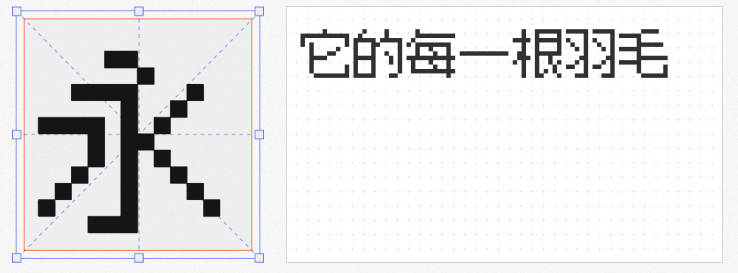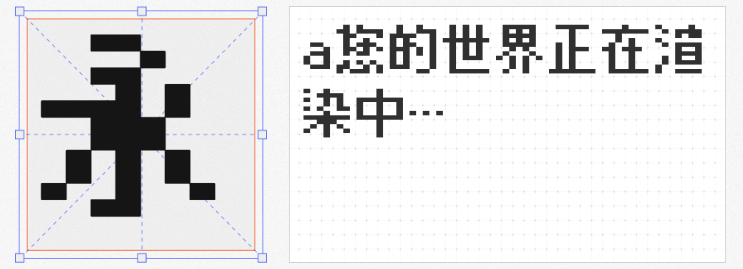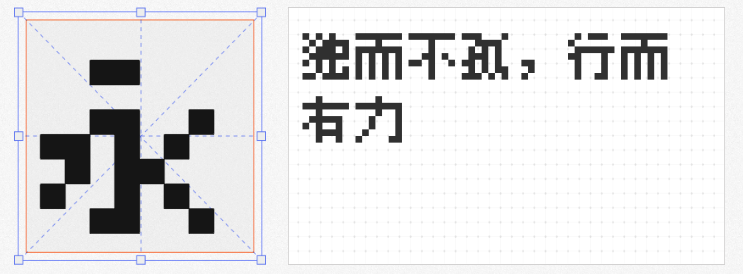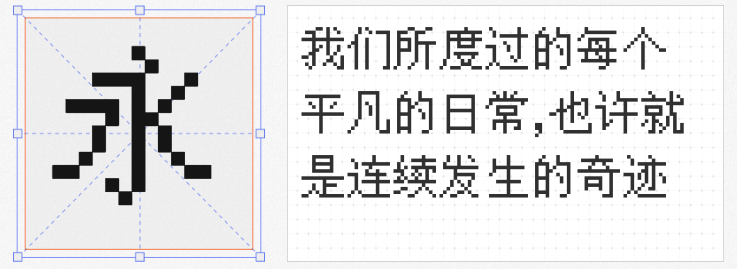
在游戏开发中,像素字体不仅是视觉风格的核心载体,更是构建沉浸式体验的关键元素。本文精选四款开源免费商用像素字体,从技术特性到应用场景,为开发者提供实用指南。
作为专为游戏设计的开源字体,方舟像素采用黑体无衬线风格,支持10/12/16px三种尺寸。其12px版本特别针对繁体中文(zh_TW)进行优化,完整覆盖中日韩统一表意文字扩展区,包含游戏界面常用的日文假名与韩文字符。字体采用SIL OFL 1.1协议授权,开发者可自由修改字形或嵌入商业游戏。在横版卷轴游戏中,该字体的等宽特性可确保对话框文字对齐,而12px的适中尺寸在4K分辨率下仍保持清晰锐利。
这款覆盖GB18030标准的自由字体,以13px尺寸成为RPG游戏对话系统的理想选择。其27842个汉字点阵经过手工优化,在1080P分辨率下呈现如印刷体般的清晰度。字体包含五组字号(9-12pt),开发者可根据UI层级灵活切换。在模拟经营类游戏中,13px宋体的衬线设计可增强菜单文字的可读性,而日文假名与韩文字符的完整支持,使其成为国际化发行的优选方案。
作为方舟像素的过渡方案,缝合怪通过合并多个开源字体实现8/10/12px三尺寸支持。其8px版本专为低分辨率设备优化,在320×240分辨率下仍能保持文字轮廓完整。在Roguelike游戏中,该字体的等宽模式可确保ASCII字符精确对齐,而10px比例模式则适合显示物品描述。需注意10px版本包含部分未明确版权来源的字形,建议仅用于非商业原型开发。
基于k8x12点阵的Flat版本通过横向拉伸1.5倍,解决传统像素字体在宽屏设备上的显示畸变问题。在赛博朋克风格游戏中,该字体的霓虹灯效果可通过颜色替换实现,而8px的极简设计特别适合模拟CRT显示器纹理。字体采用OFL协议授权,支持通过配置文件调整基线位置,开发者可轻松创建自定义变体。